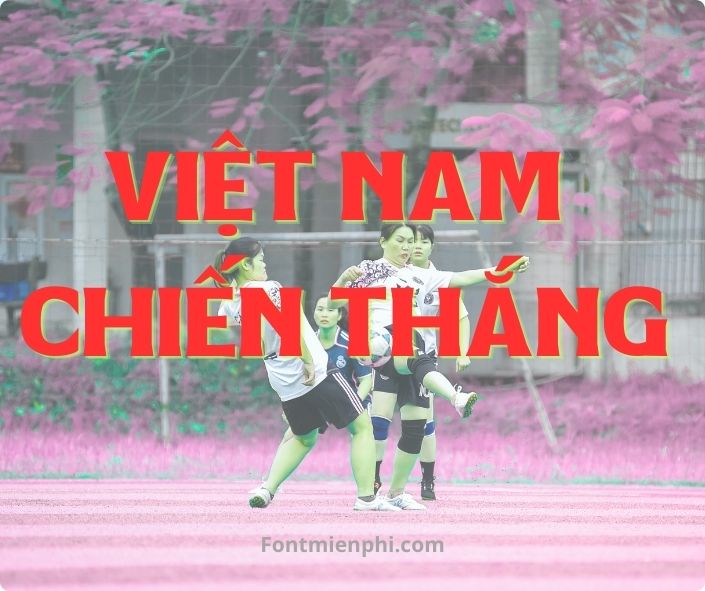
Font Việt hóa VIP Goldener
Bạn đang tìm kiếm một phông chữ mang đậm nét sang trọng, tinh tế và cổ điển cho dự án thiết kế của mình? Font Việt hóa VIP Goldener chính là mảnh ghép hoàn hảo mà bạn đang thiếu. Đây là một bộ font Serif tuyệt đẹp, đã được việt hóa trọn bộ và căn chỉnh tỉ mỉ từng dấu câu. Phông chữ này cực kỳ lý tưởng để ứng dụng vào thiết kế logo thương hiệu, thiệp cưới cao cấp, bao bì sản phẩm hay các ấn phẩm truyền thông mang phong cách hoàng gia. Khám phá và tải ngay font Goldener Việt hóa để nâng tầm đẳng cấp cho các thiết kế của bạn!
rong thế giới thiết kế đồ họa (Graphic Design), việc lựa chọn đúng phông chữ đóng vai trò quyết định đến sự thành công của một ấn phẩm. Nếu bạn là người đam mê những đường nét thanh lịch, cổ điển nhưng không kém phần quyền lực, thì Font Việt hóa VIP Goldener chắc chắn là một cái tên không thể bỏ qua trong bộ sưu tập typography của bạn.
Đặc điểm nổi bật của Font VIP Goldener
Goldener vốn là một typeface thuộc dòng Serif (chữ có chân) mang phong cách vương giả. Điểm nhấn của font chữ này nằm ở độ tương phản cao giữa các nét thanh và nét đậm, kết hợp cùng những đường lượn sóng mềm mại ở phần chân chữ.
Ở phiên bản Font VIP Goldener Việt hóa, các designer sẽ không còn phải đau đầu về tình trạng lỗi font hay dấu câu bị lệch khi gõ tiếng Việt. Bộ font đã được xử lý kỹ lưỡng:
• Kerning chuẩn xác: Khoảng cách giữa các ký tự và dấu câu tiếng Việt được tinh chỉnh hài hòa, mang lại cảm giác dễ chịu cho thị giác.
• Giữ nguyên sắc thái bản gốc: Các dấu câu được thiết kế đồng bộ với phong cách cổ điển của bộ phông chữ, không làm mất đi vẻ đẹp sang trọng ban đầu.
• Hỗ trợ Alternate Glyphs: Nhiều ký tự thay thế tuyệt đẹp giúp bạn tha hồ sáng tạo nên những đoạn text mang đậm tính nghệ thuật.
Tính ứng dụng của Font Goldener Việt hóa
Với vẻ đẹp kiêu sa của mình, phông chữ này thường xuyên được các nhà thiết kế ưu ái sử dụng trong các dự án đòi hỏi tính thẩm mỹ cao:
• Thiết kế nhận diện thương hiệu (Branding): Rất phù hợp làm logo cho các thương hiệu thời trang cao cấp, mỹ phẩm, trang sức, nhà hàng fine-dining hoặc khách sạn 5 sao.
• Thiết kế thiệp cưới (Wedding Invitations): Goldener mang lại sự lãng mạn, trang trọng và chỉn chu cho những tấm thiệp cưới hiện đại pha lẫn cổ điển.
• Bao bì sản phẩm (Packaging): Ứng dụng tuyệt vời trên các nhãn chai rượu vang, hộp trà cao cấp hoặc hộp quà tặng VIP.
• Thiết kế tạp chí & Lookbook: Sử dụng làm tiêu đề (Headline) để tạo điểm nhấn quyền lực cho các trang bìa tạp chí thời trang.